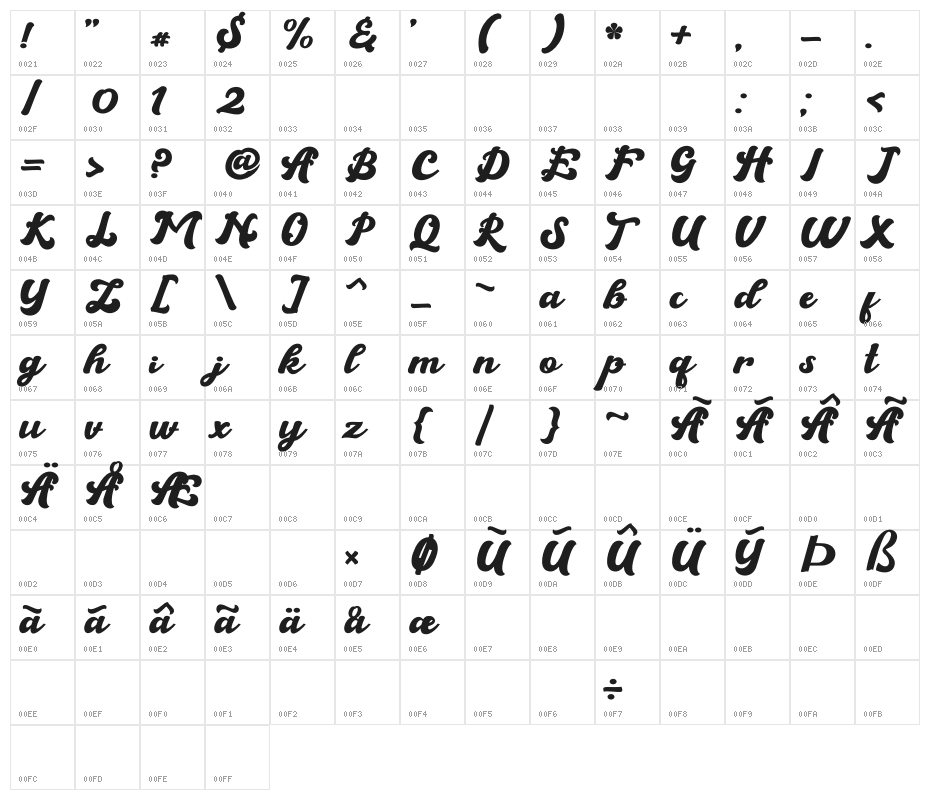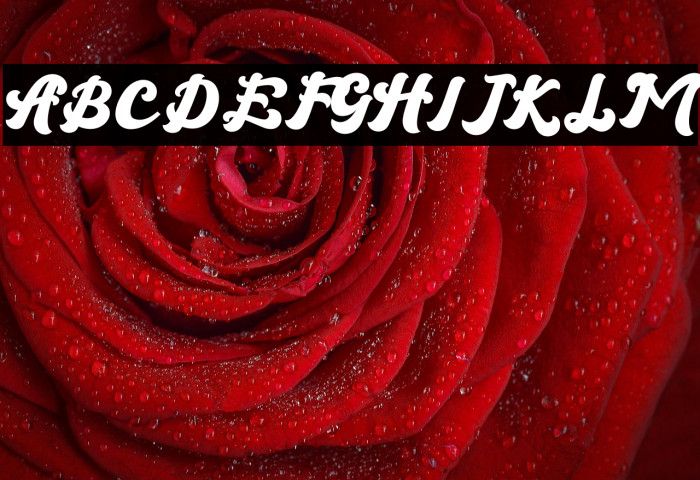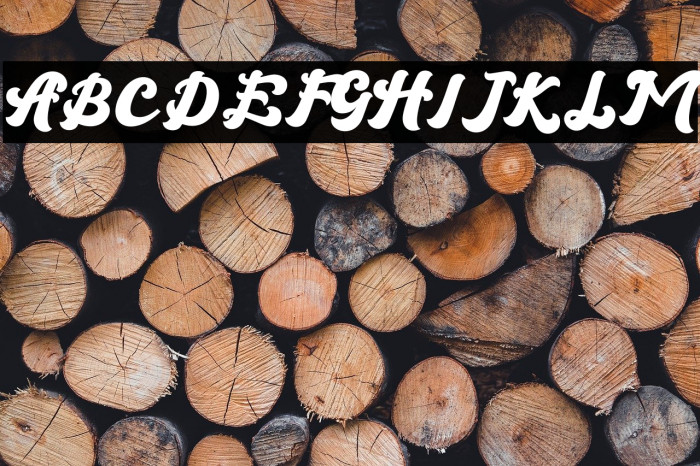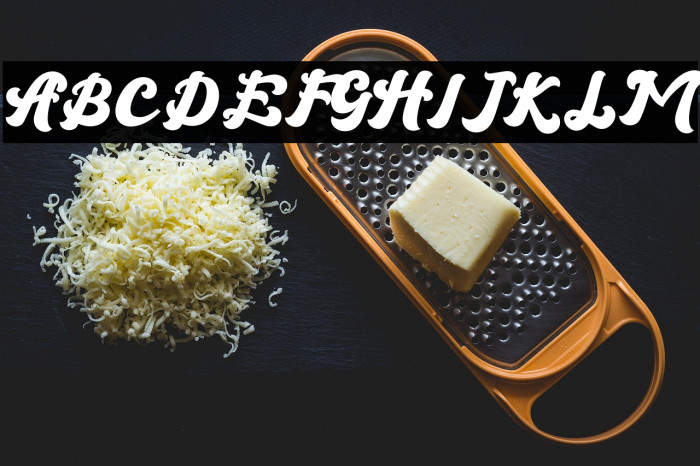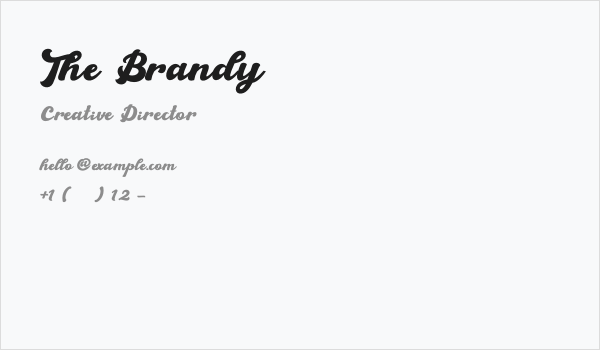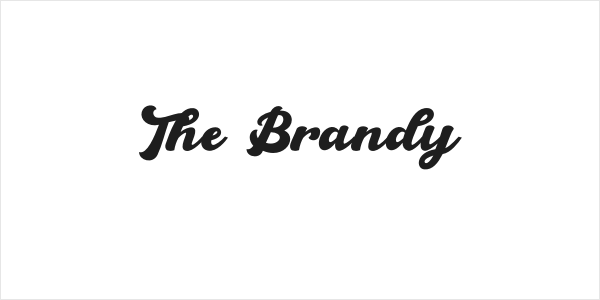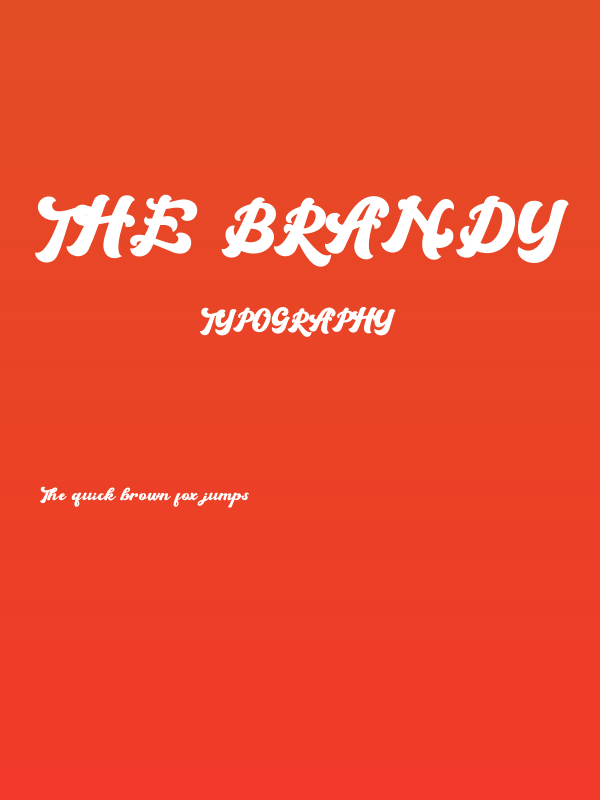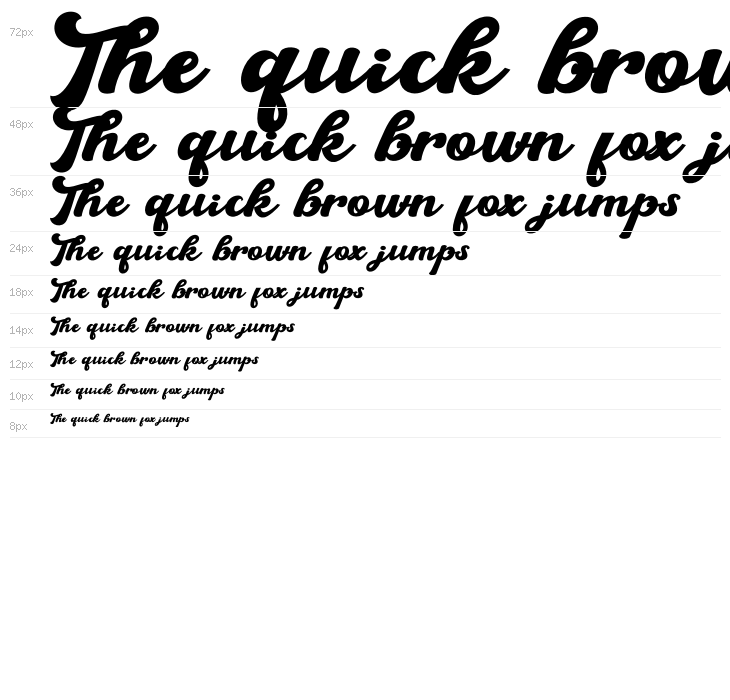
The Brandy Font
| Caso d'uso | Logos, Invitations, Decorative Headlines |
| Progetti proposti | Ideal for branding, invitations, and decorative headlines where a bold, elegant script is desired. |